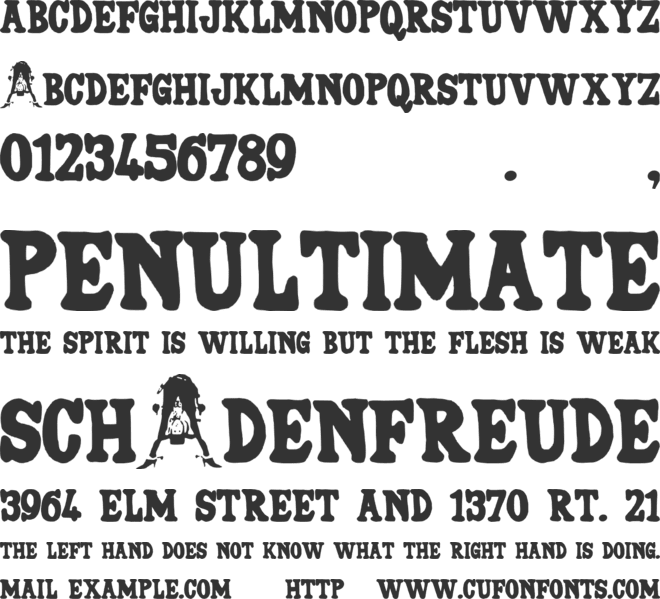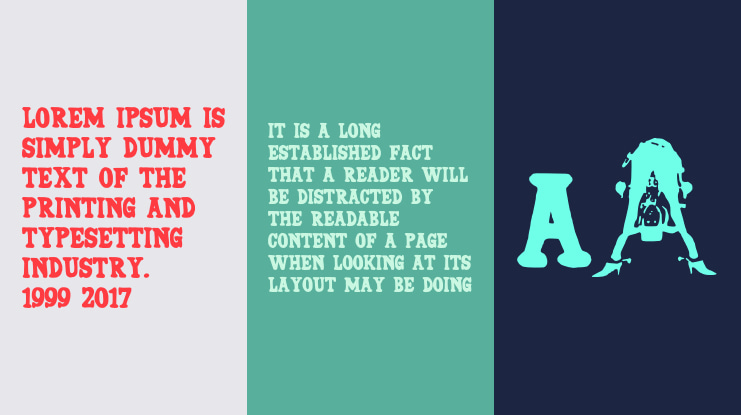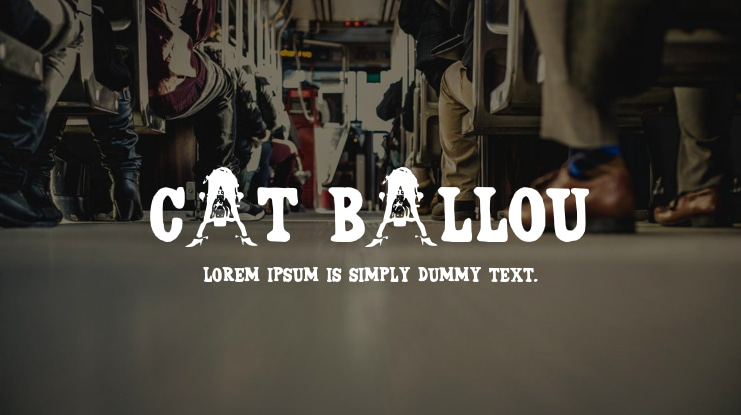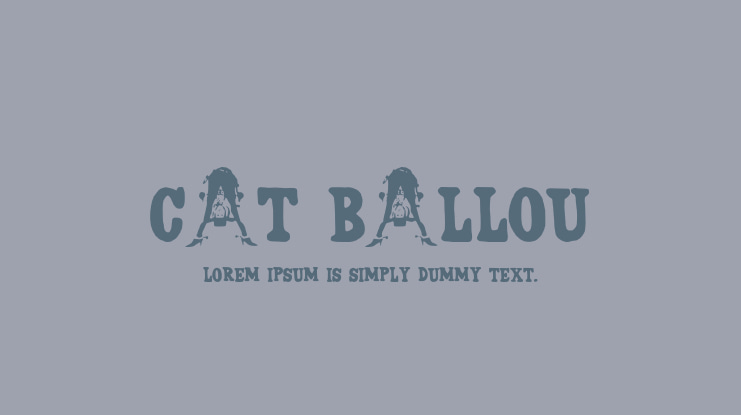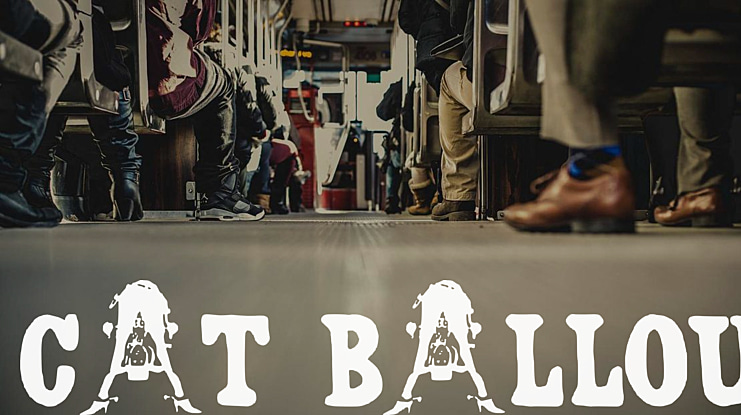
CAT BALLOU Font
P.A.Vannucci
direttamente dal film diretto da Elliot Silverstein e interpretato da Jane Fonda, il font inedito per tutti gli estimatori del film. Da notare il ritocco necessario in Photoshop per conferire, alla titolazione, l'originale bordatura.
directly from the Best movie by Elliot Silverstein, with Jane Fonda, the original font for all lovers. Use ADOBE Photoshop for the original border from title.